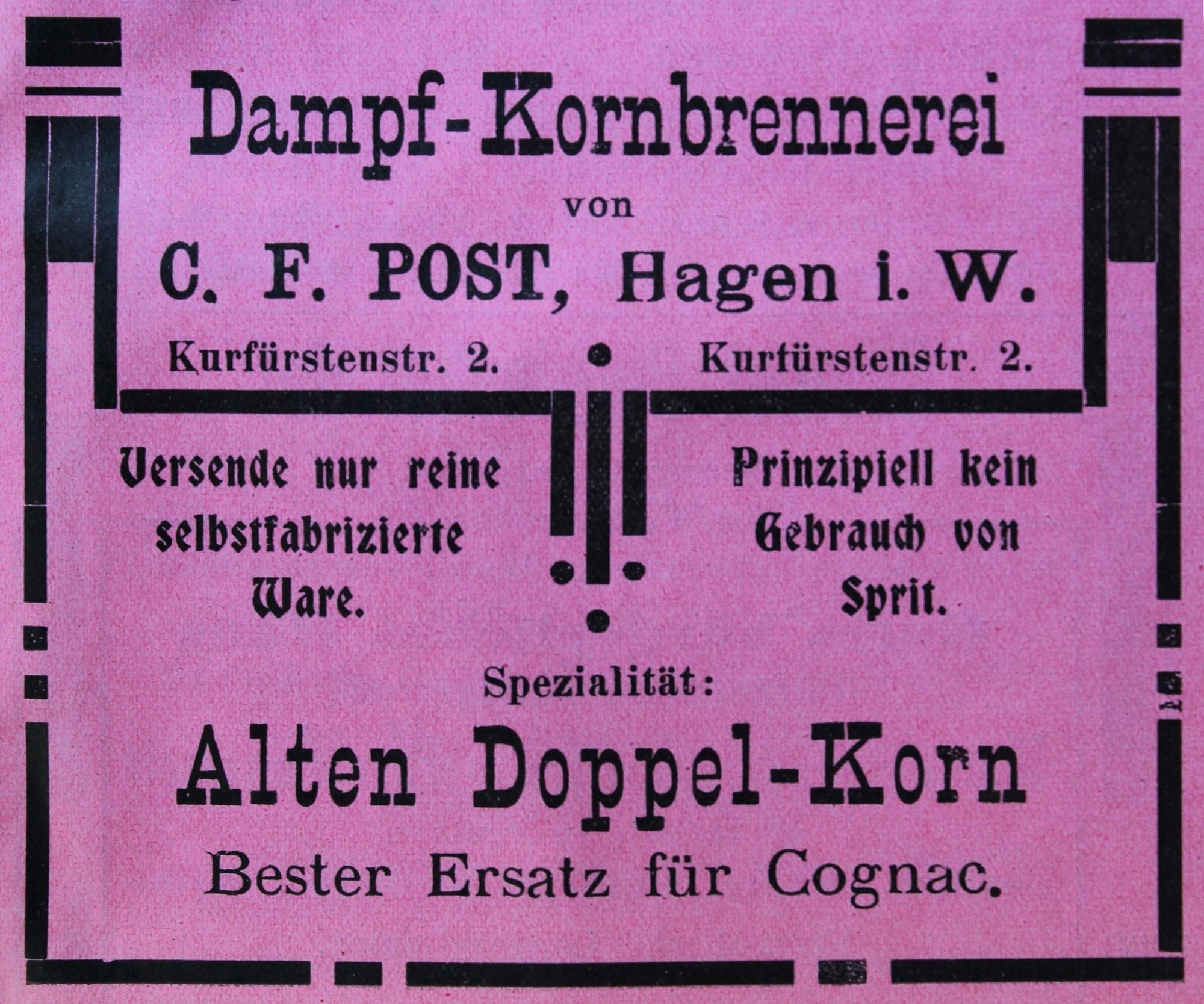
Antiqua aus den 1880er Jahren gesucht. Werbeannonce anbei.
Aus welcher Schriftart wurde der Satz "Bester Ersatz für Cognac" gesetzt?
Diese Type wird häufig als Textschrift in Büchern aus dieser Zeit verwandt.
Das ist aber nicht 1880er, sondern später? Die Bradley/Altgotische ist aus der Mitte der 1890er, genauer aus dem Jahr 1895. (Versende nur ..., Kein Gebrauch von ... ) Die Anzeige sollte also frühestens 1895 gedruckt worden sein, eher sogar später. Der Ersatzcognac ist sehr wahrscheinlich eine eher individuelle Interpretation der Didot und/oder ggf. Bodoni? Das deutet auf eine eher schlecht ausgestattete Druckerei hin? Und die wird die Bradley sehr wahrscheinlich nicht bereits kurz nach dem Erscheinen eingekauft haben?
C. F. Post ist so was ähnliches wie die New Century Schoolbook, welche es aber erst später (1918ff) gab. Schriften dieser Art waren aber irgend wann mal Ende des 19ten Jh. sehr modern, bis sie auf ein Mal Anfang des 20ten Jh. aus der Gunst der Druckereien gefallen sind und fast vollständig verschwanden. Ein Remake solchwer Schriften gibt es unter den Namen Old Standard als Freeware SIL-OFL. Bei der Dokumentation dazu findest Du auch diese Informationen. Siehe: https://www.fontsquirrel.com/fonts/Old-Standard-TT
Wie heißt die gesuchte Schrift?
Gibt es sie wohl digital?
In Büchern aus dieser Zeit wird sie oft als Textschrift eingesetzt (habe ich gesehen, besitze diese Bücher aber nicht).
Was haltet ihr von der "Lateinisch" von Berthold?
Gibt es sie digital?